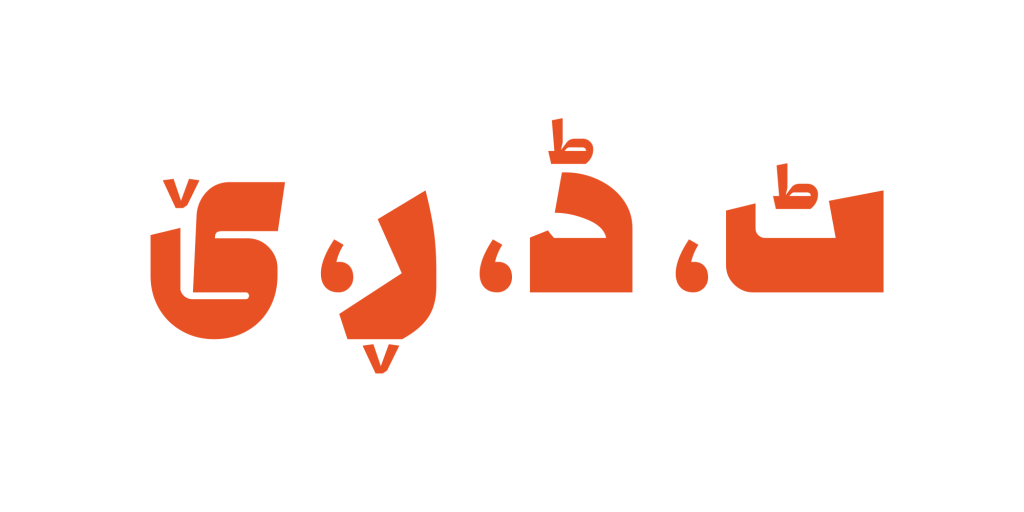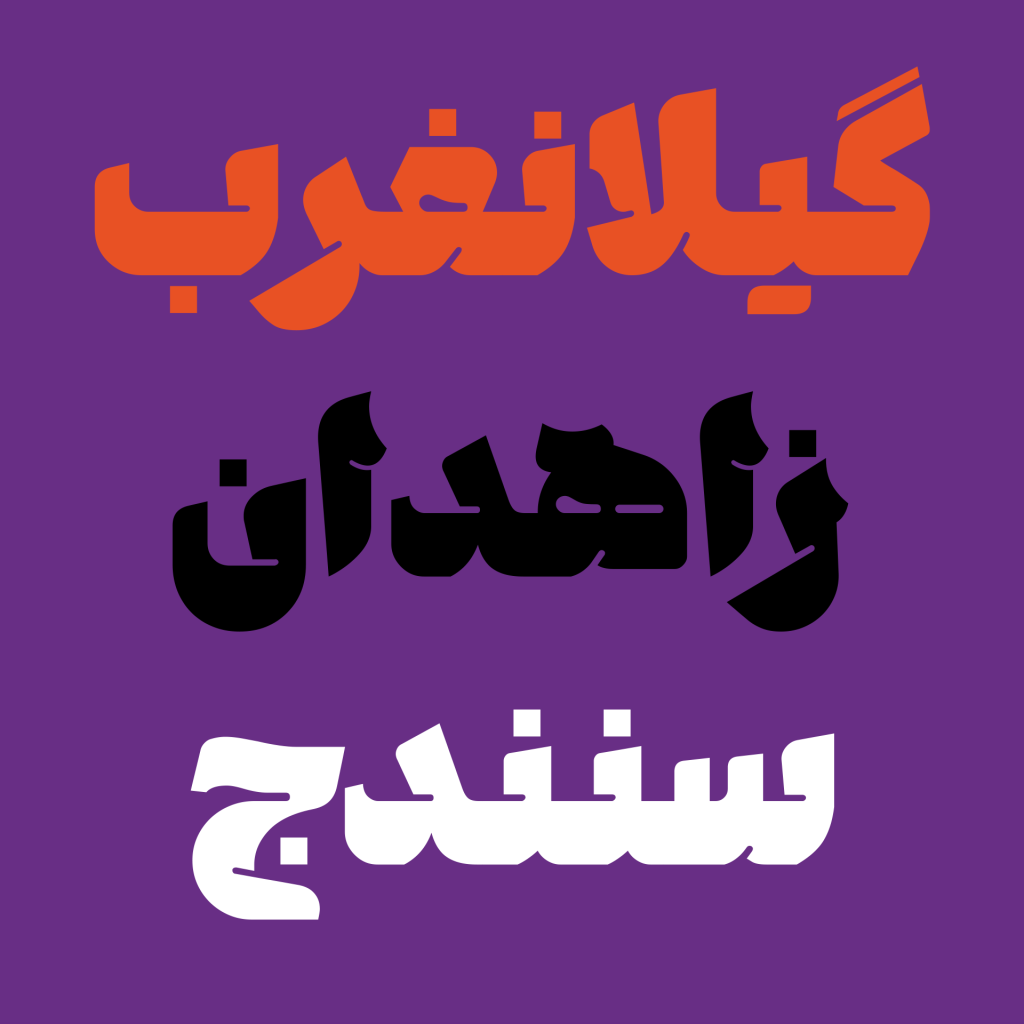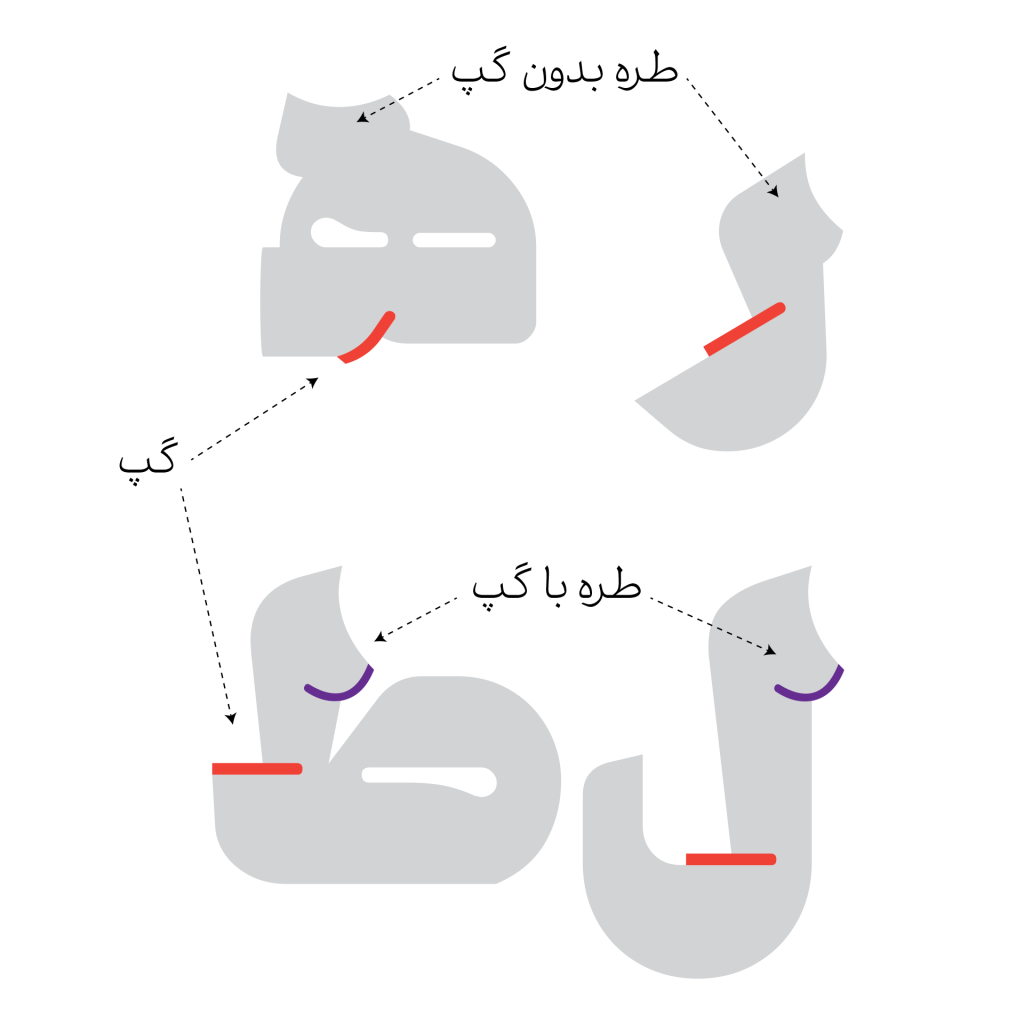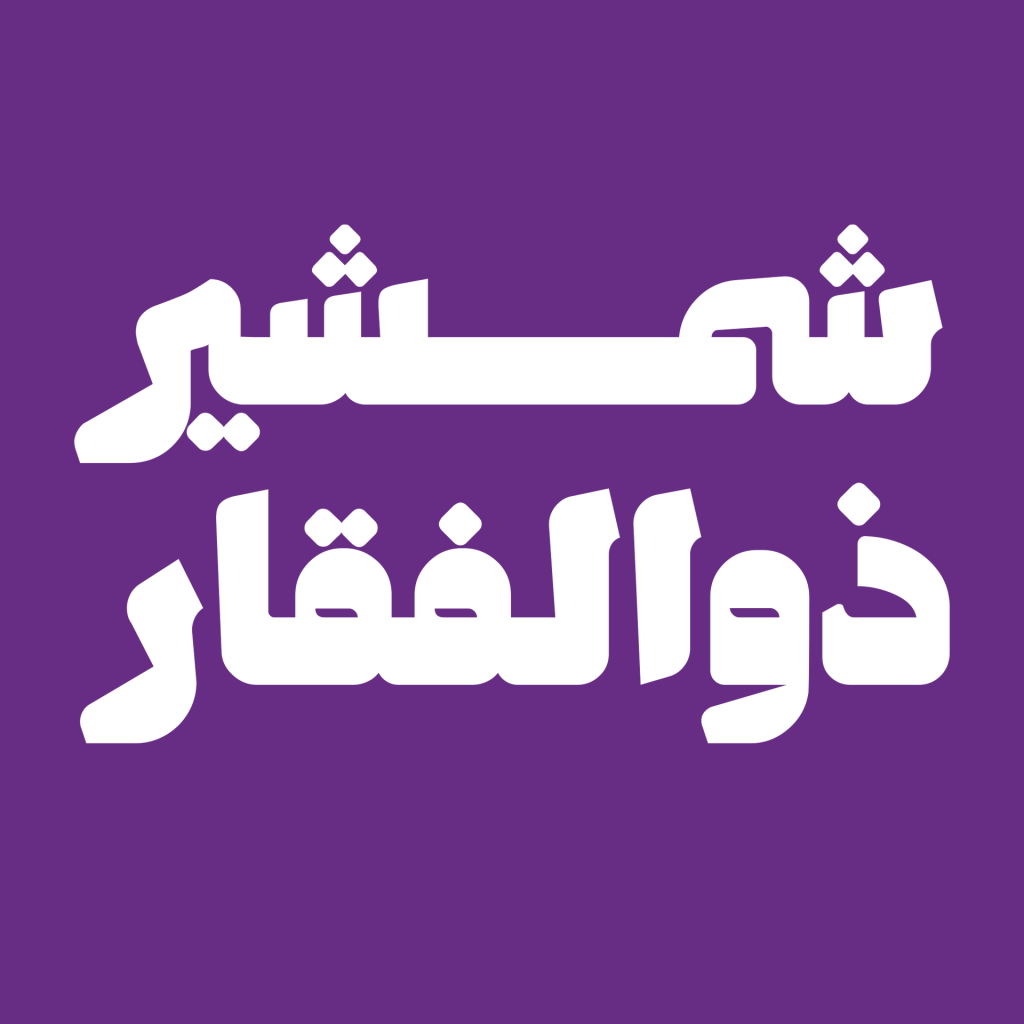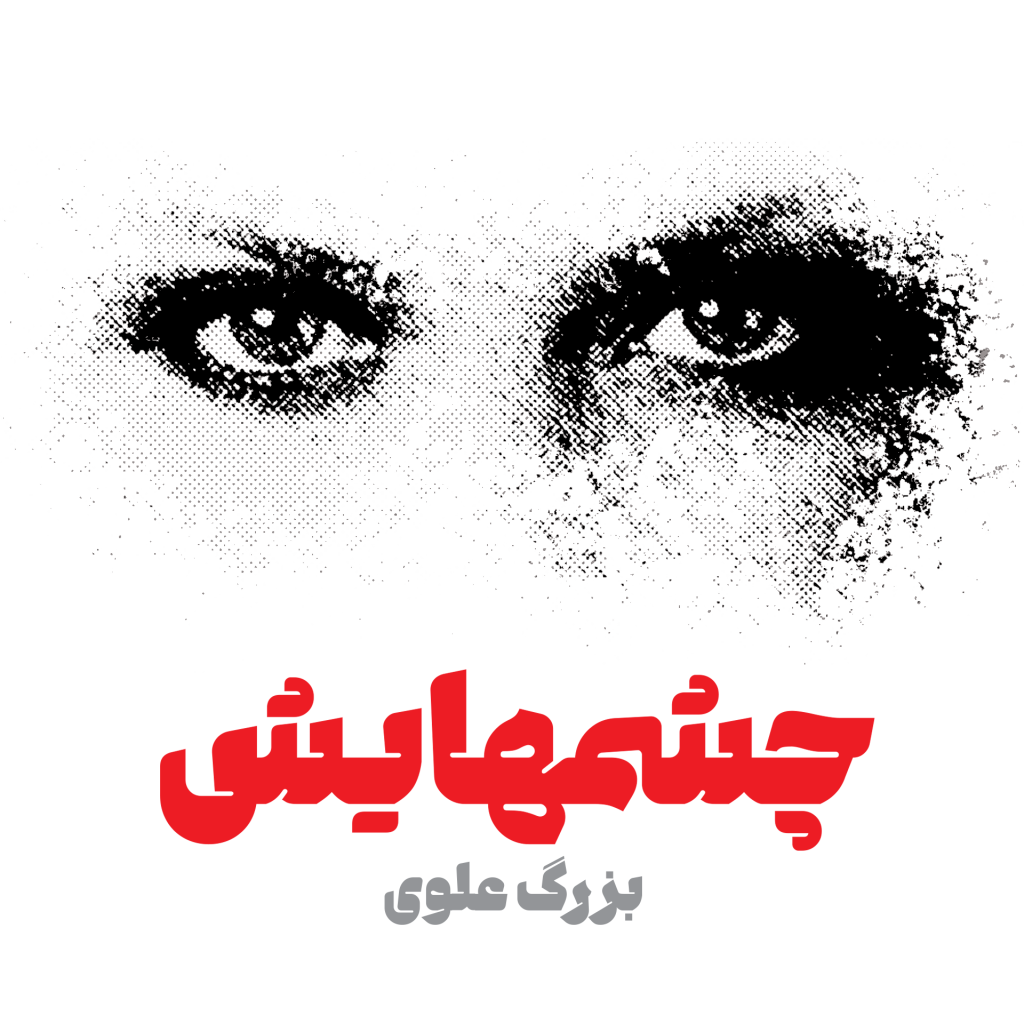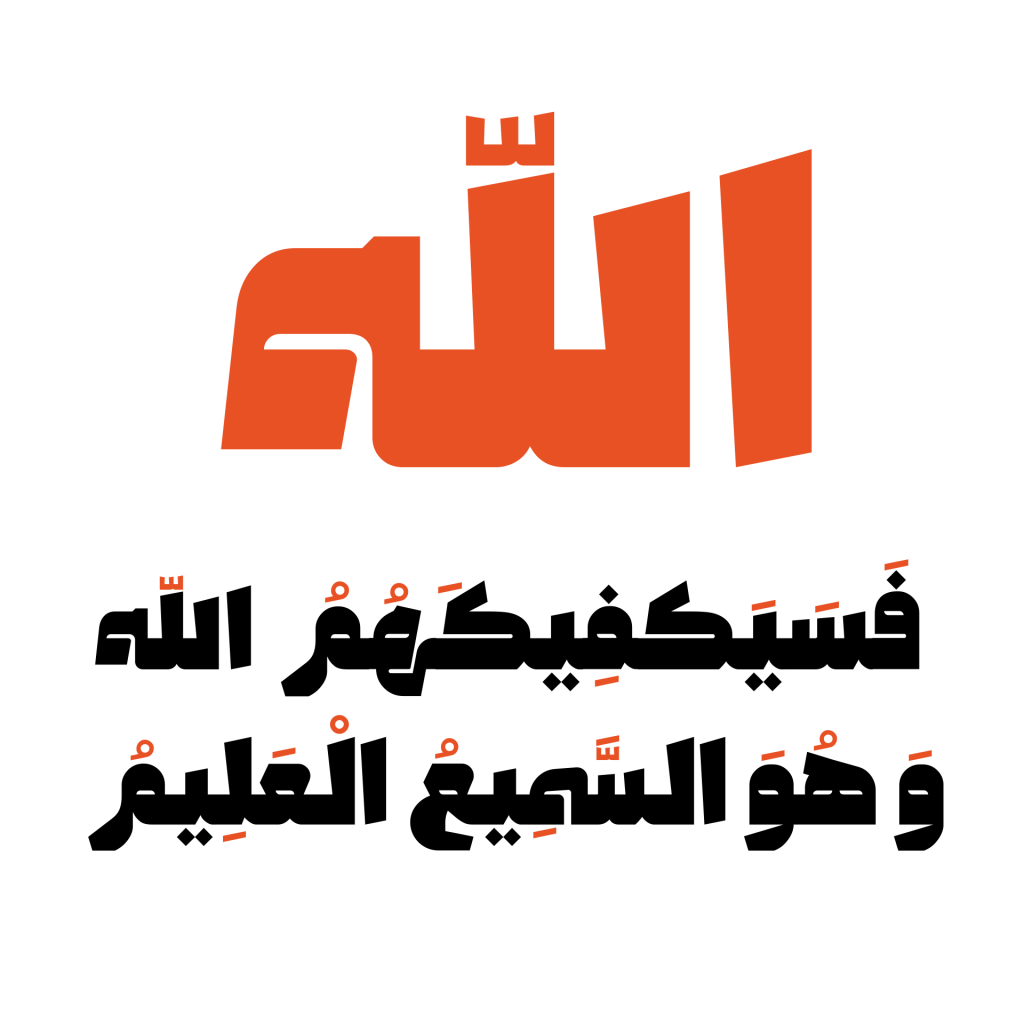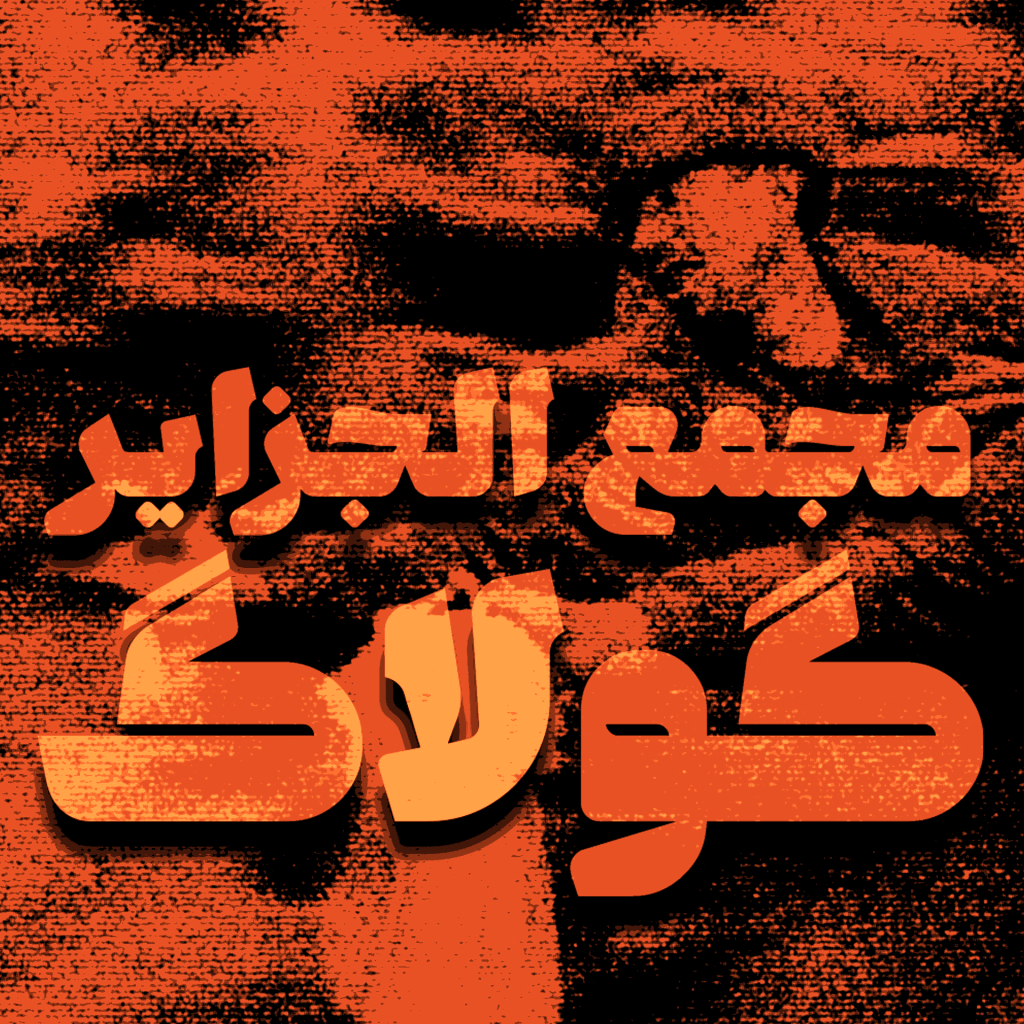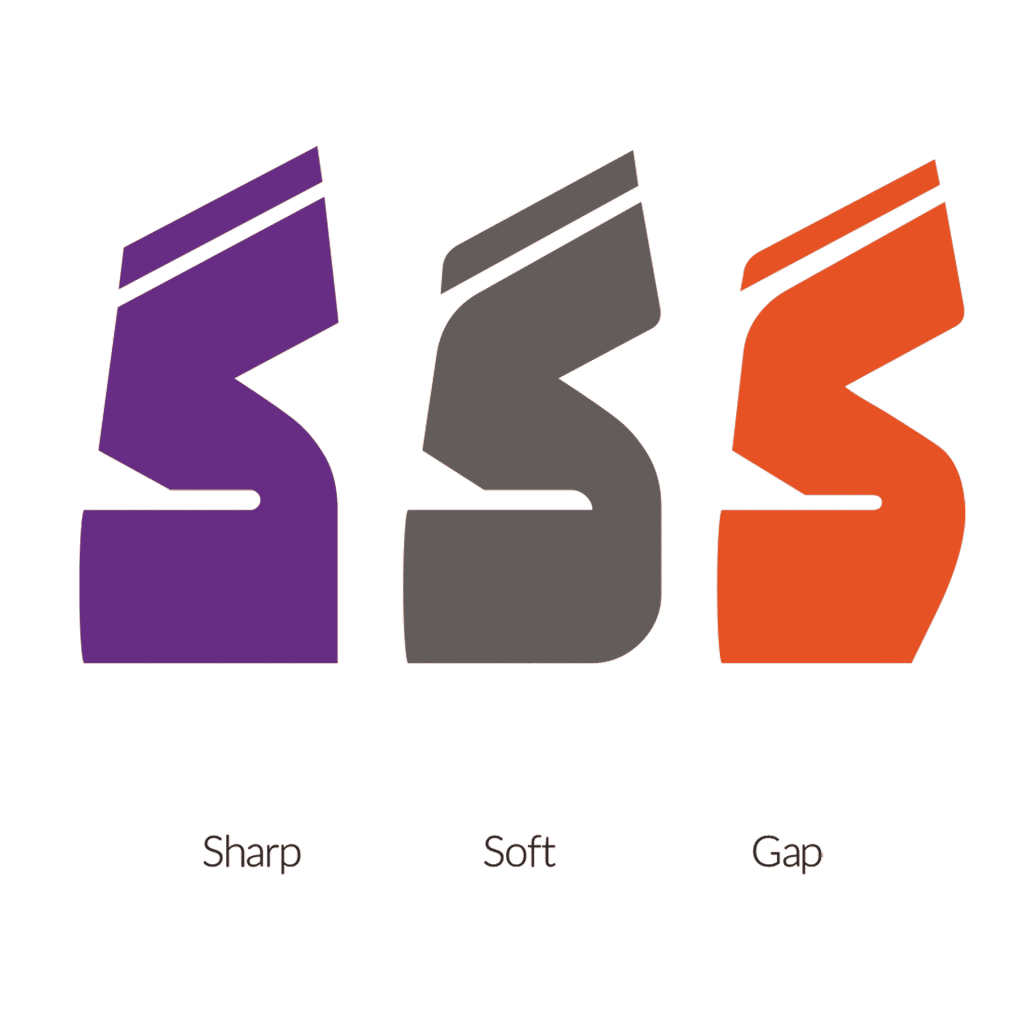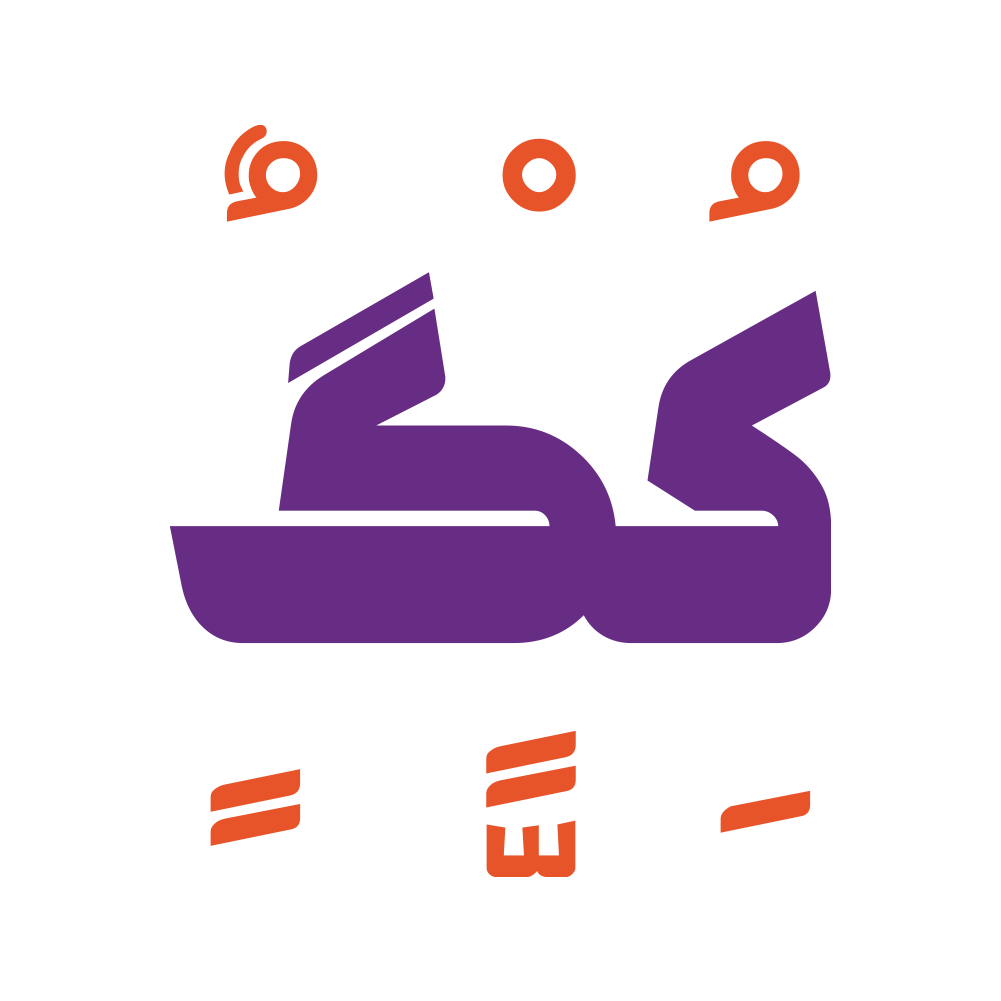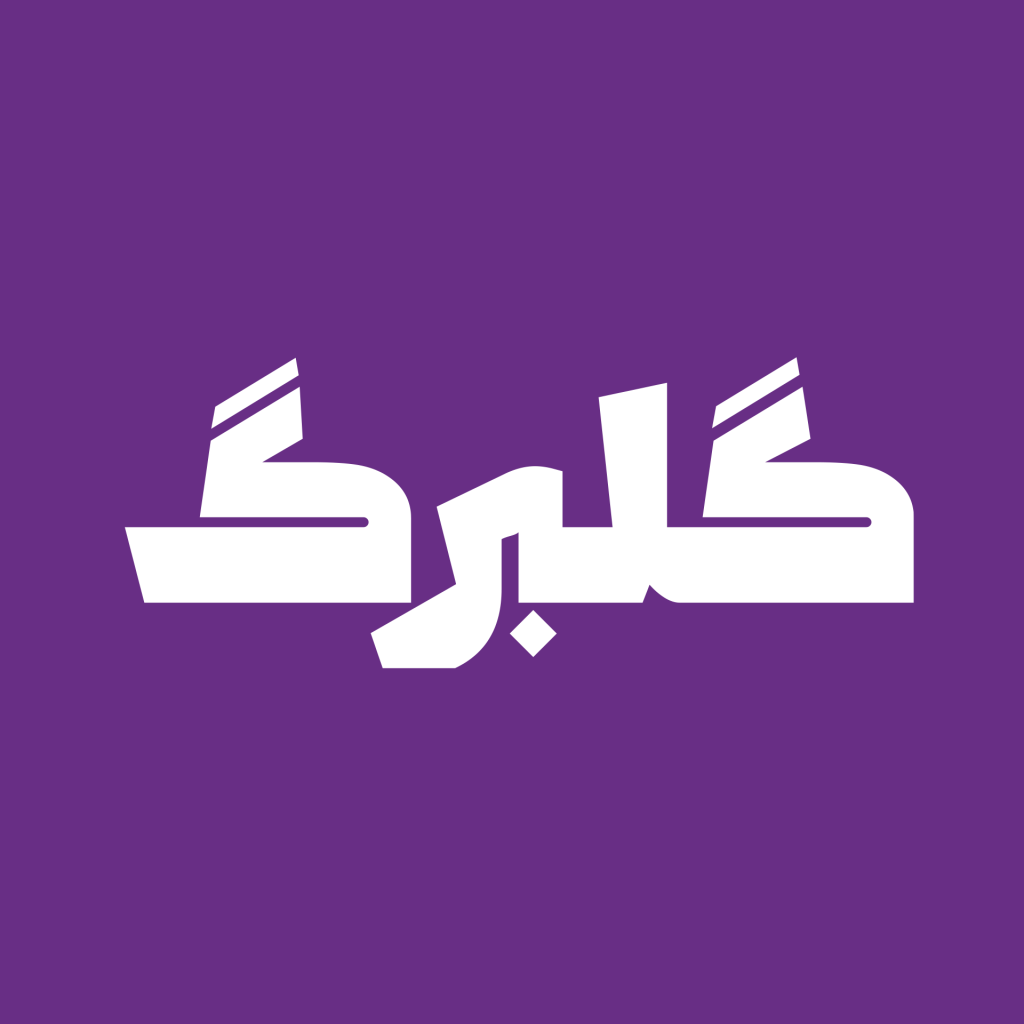
فونت وزین
فونت وزین حروف هندسی می باشد ولی فرم هر سه استايل با هم متفاوت باشد.
در واقع ساختار کلی حروف مشابه است اما با تغییراتی که در هر سبک ایجاد شده هرکدام لهجه ای و شکلی متفاوت دارد.
برای مثال: فونت وزین شارپ هندسهای خشک و رسمی دارد.
این تایپ فیس گپ با هندسهای گردتر و نرم تر بیشتر برای موارد تبلیغاتی قابل استفاده است.
این محصول از زبان های کردی، اردو، عربی و انگلیسی نیز پشتیبانی میکند.
1 وزن 3 استایل